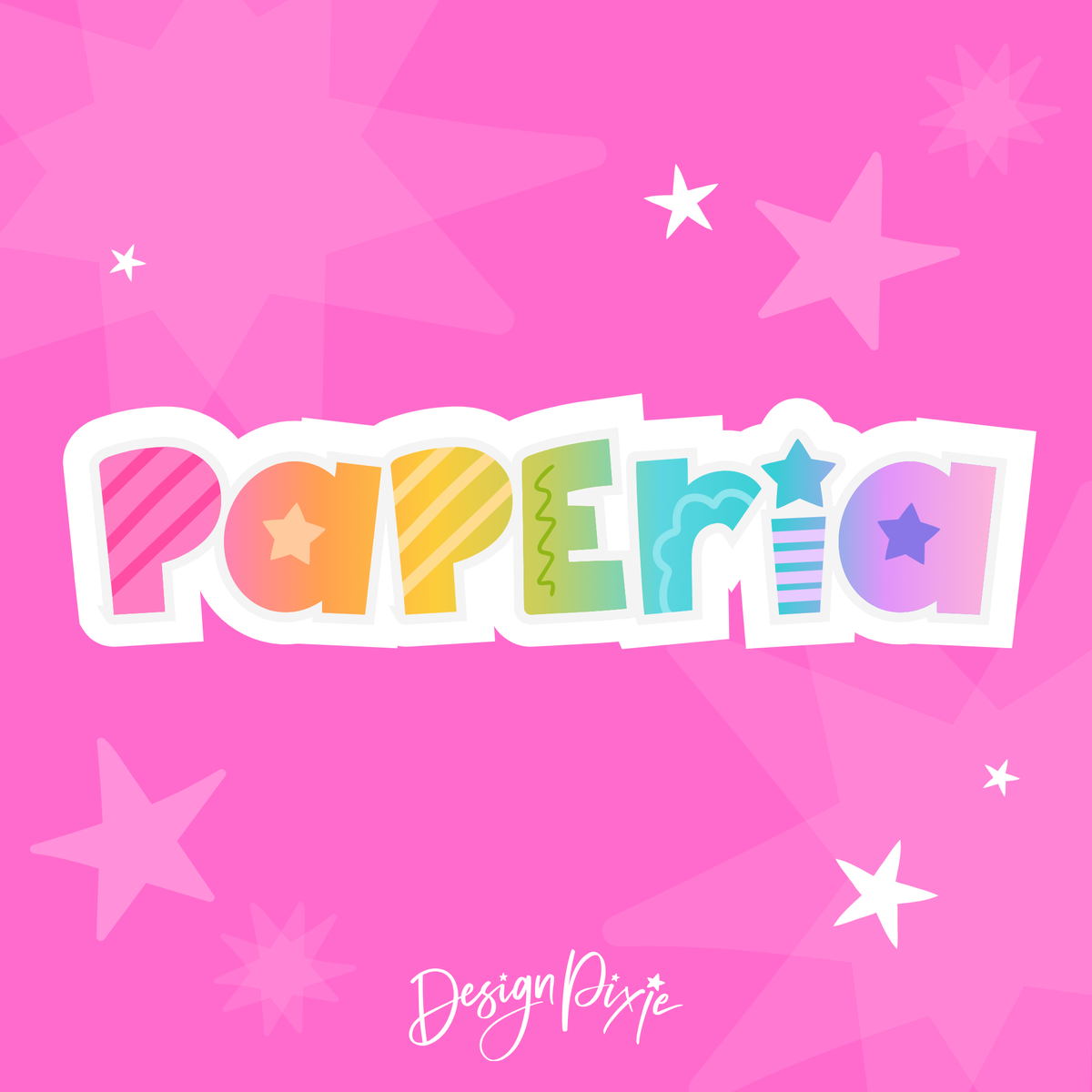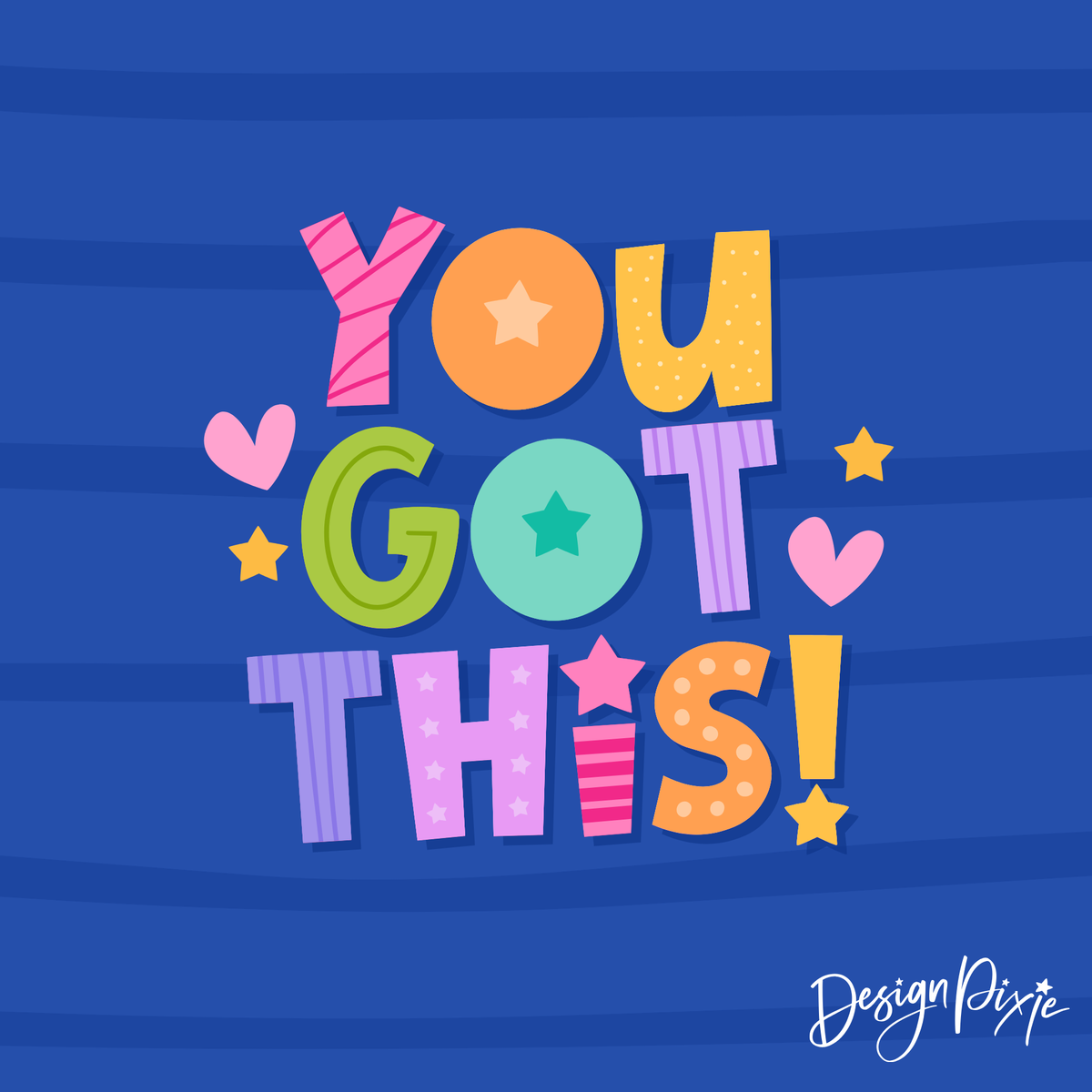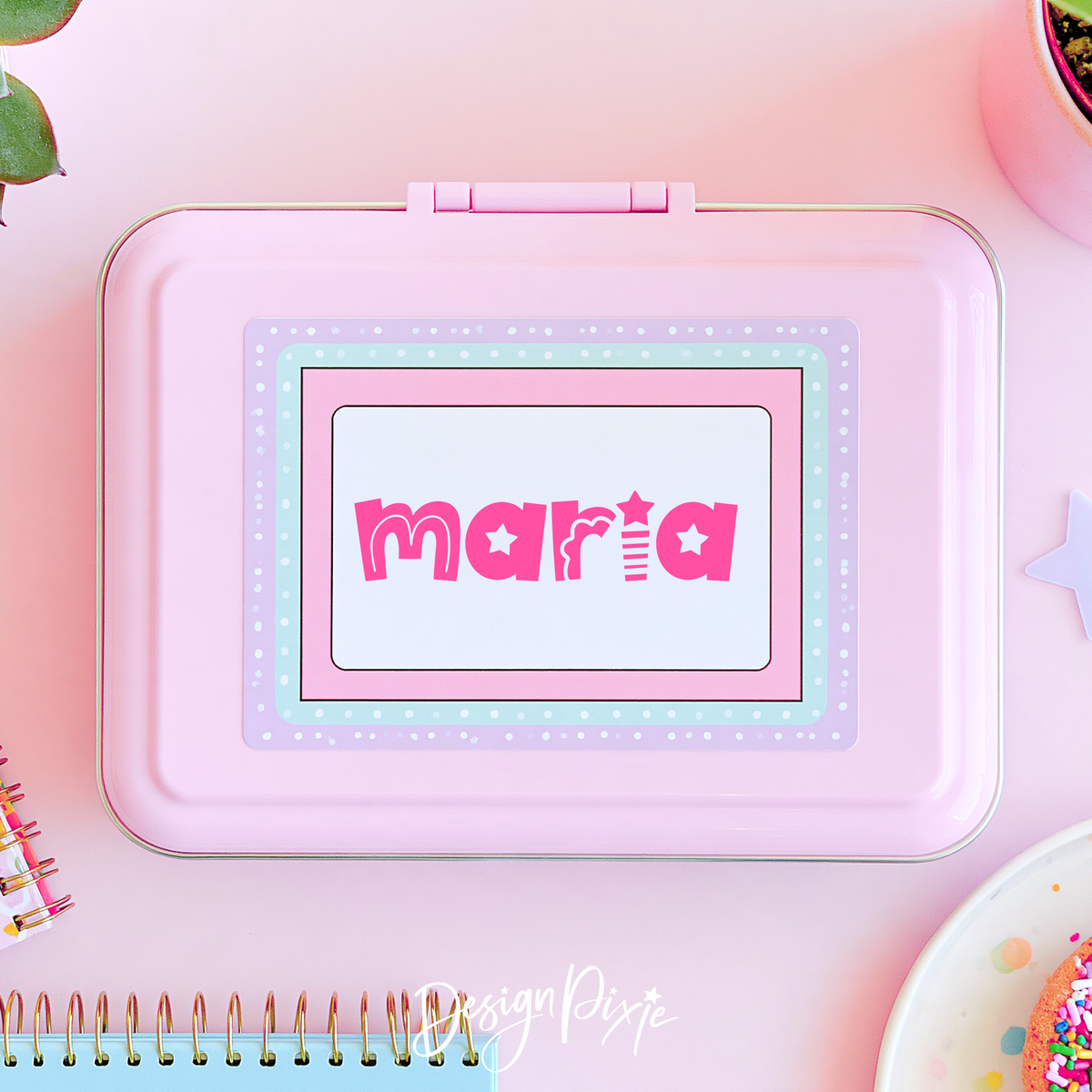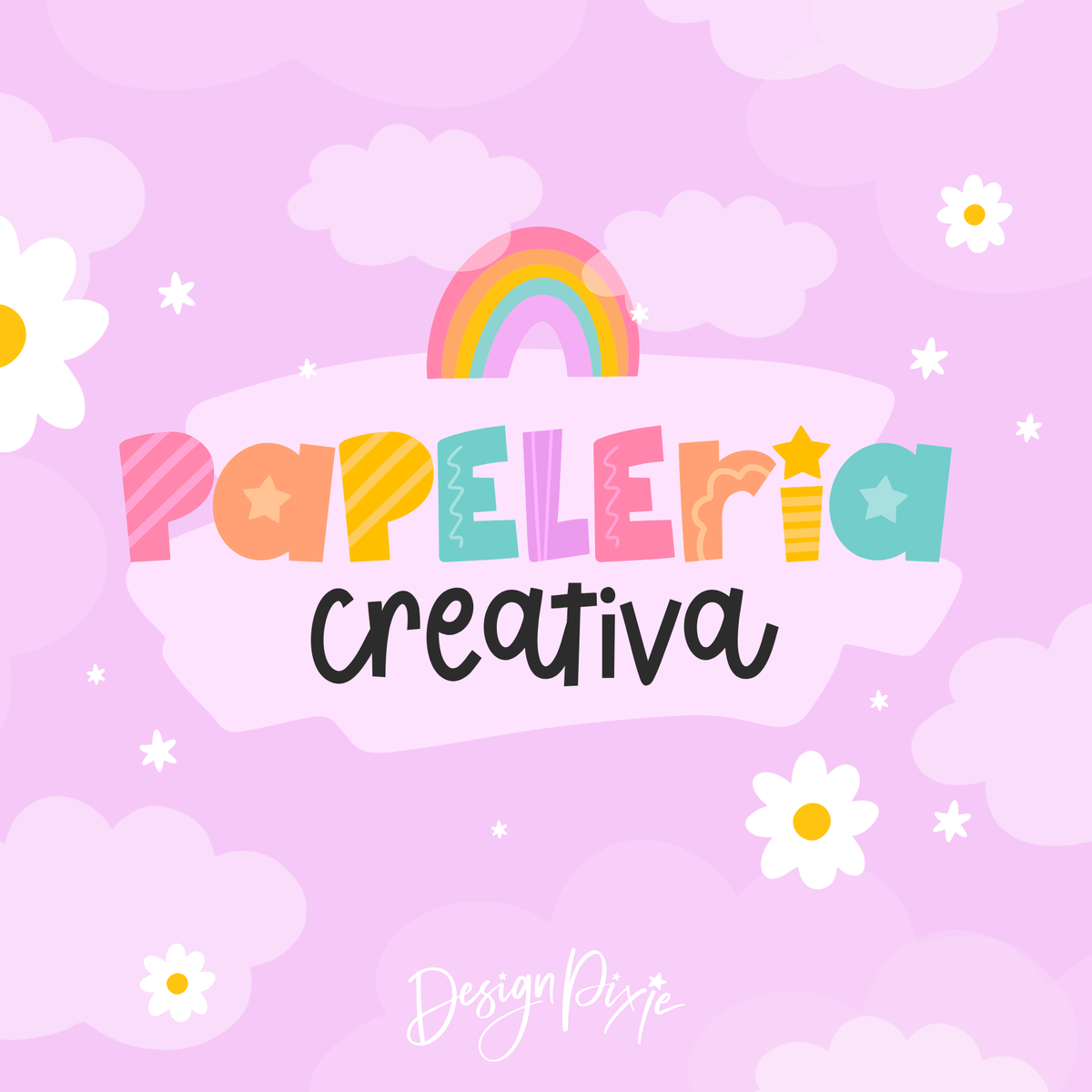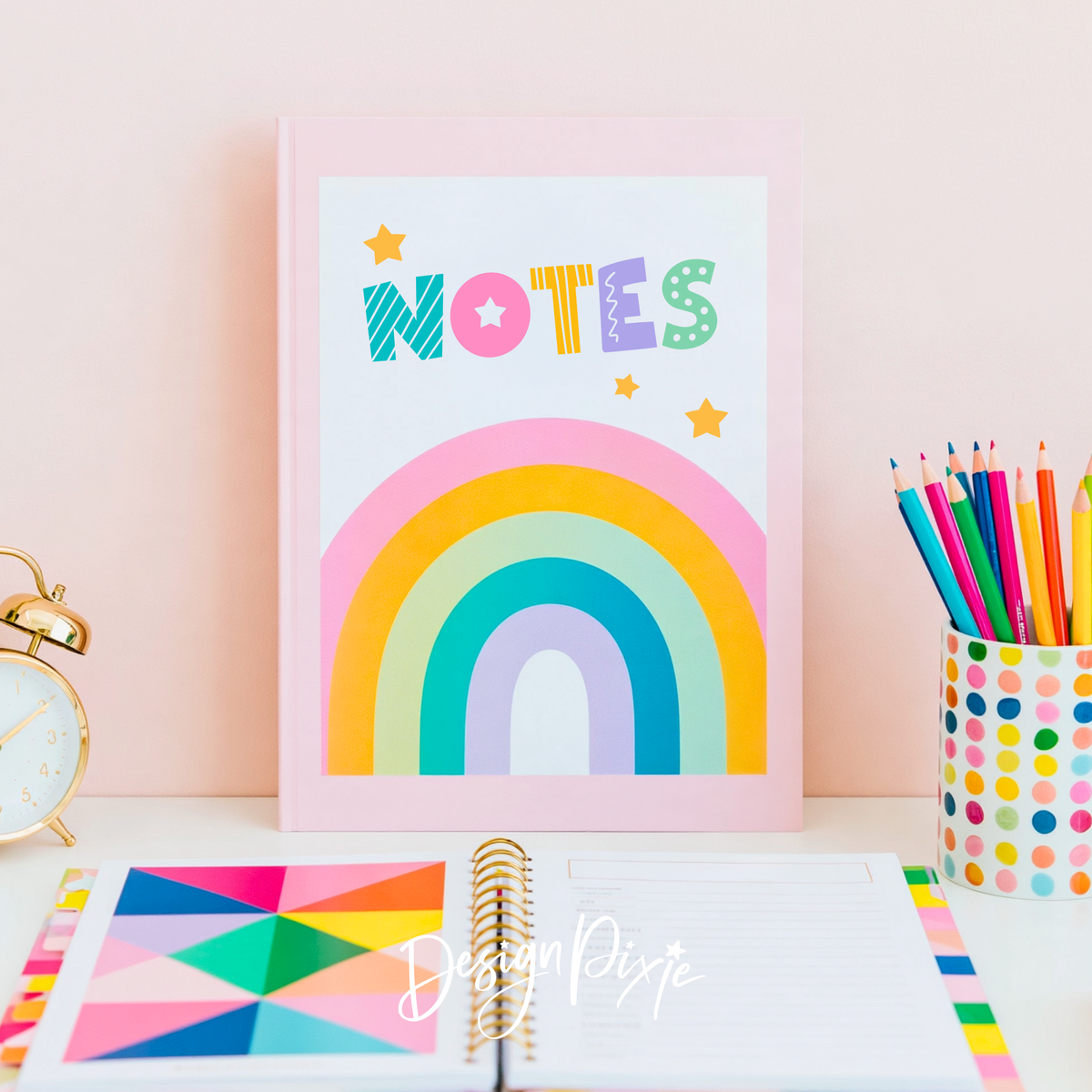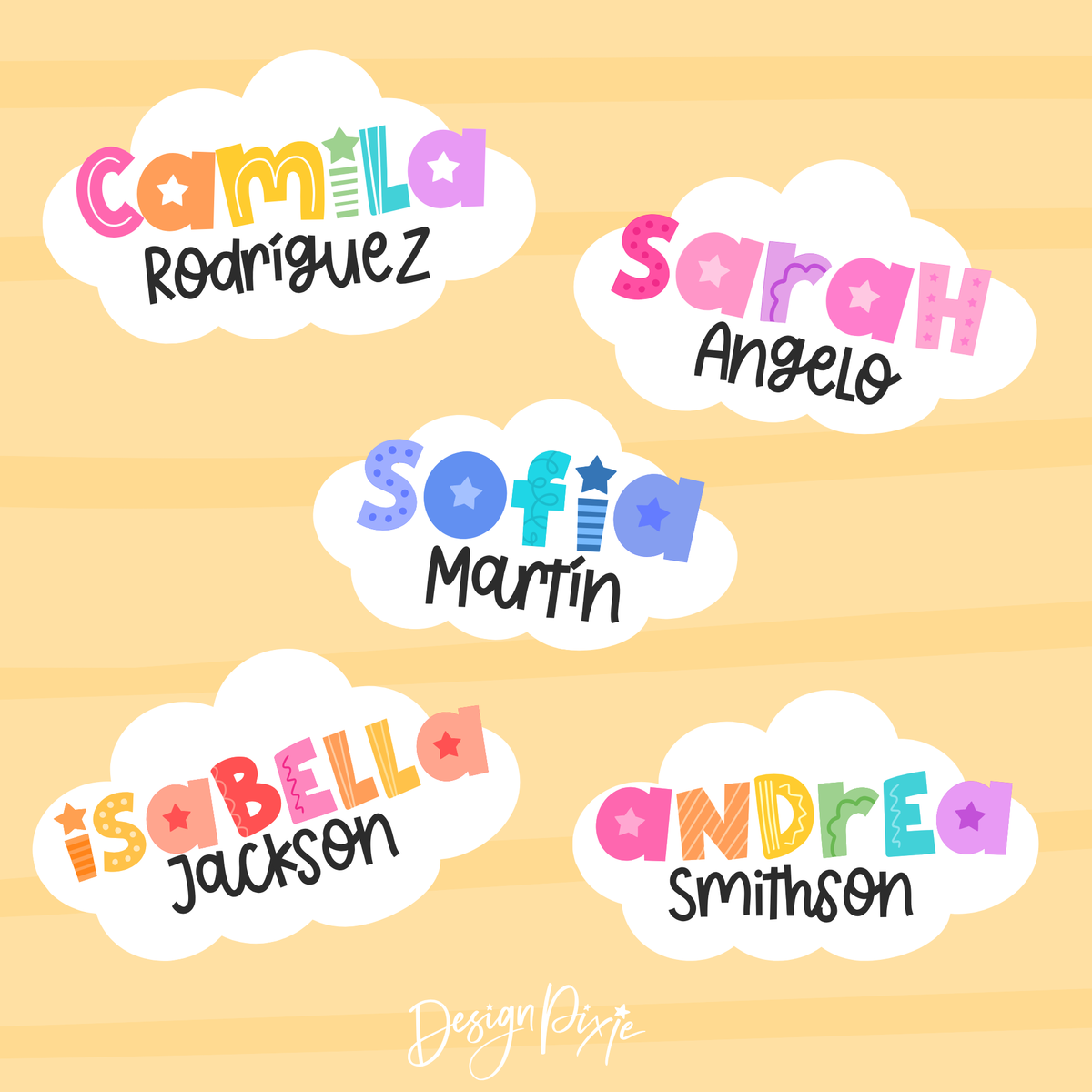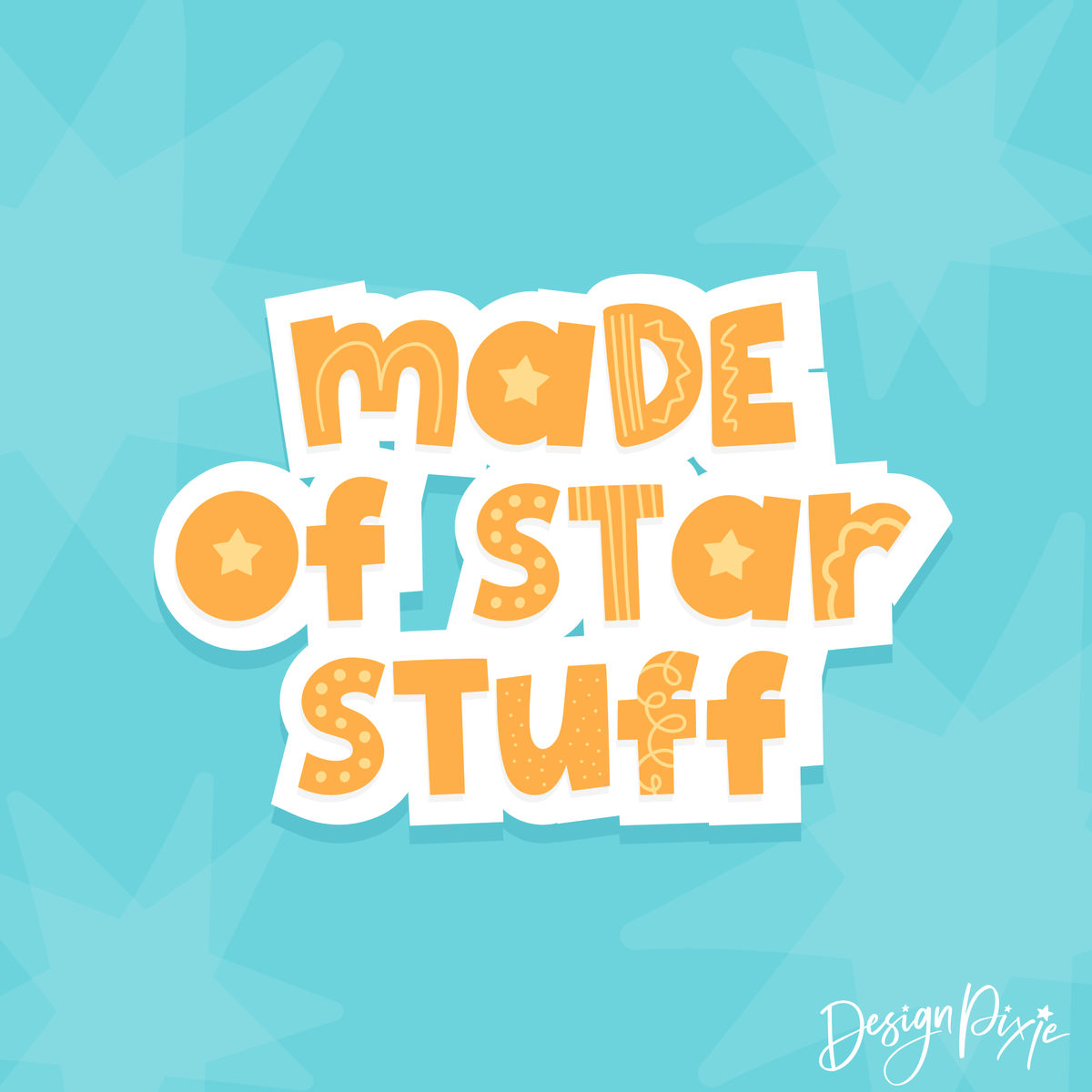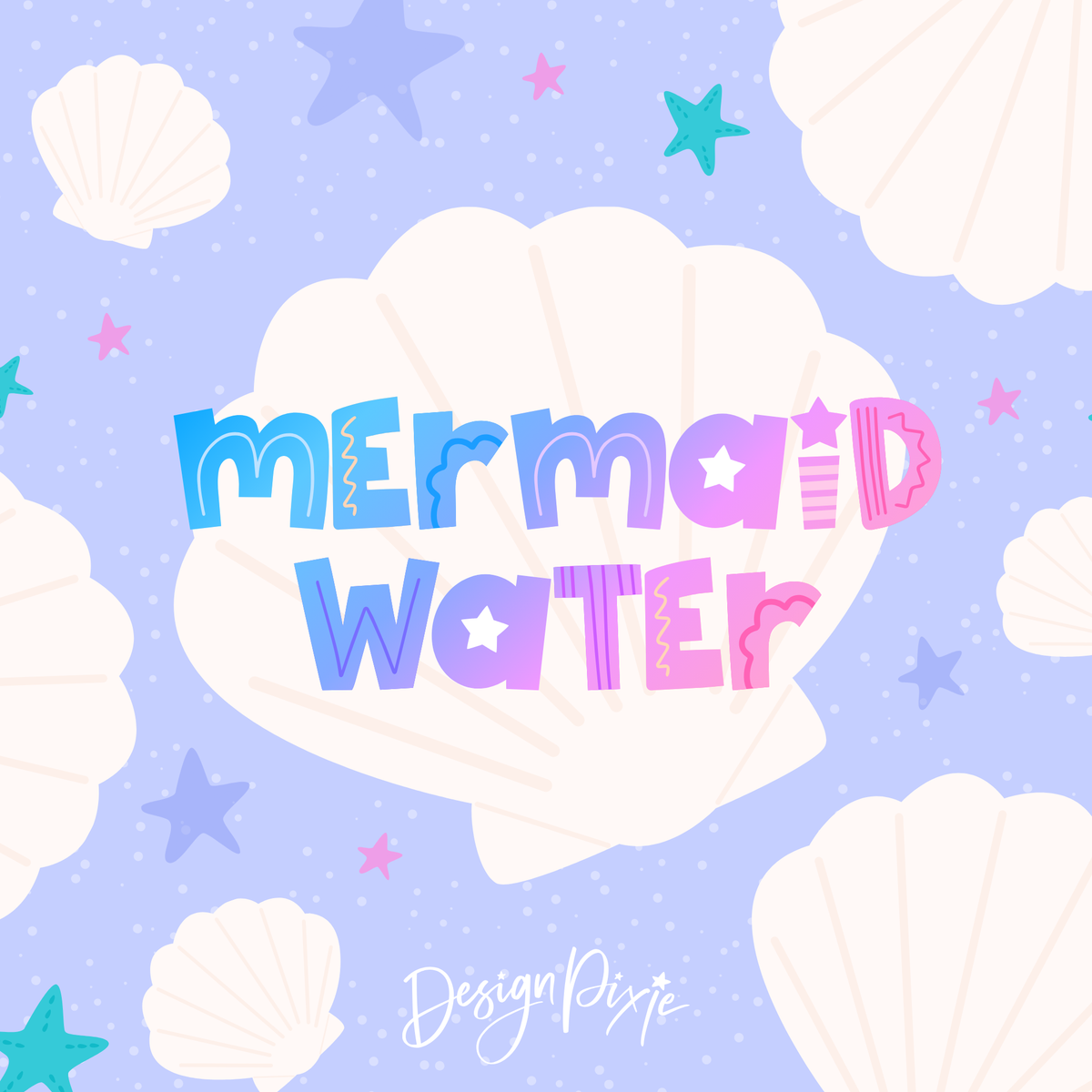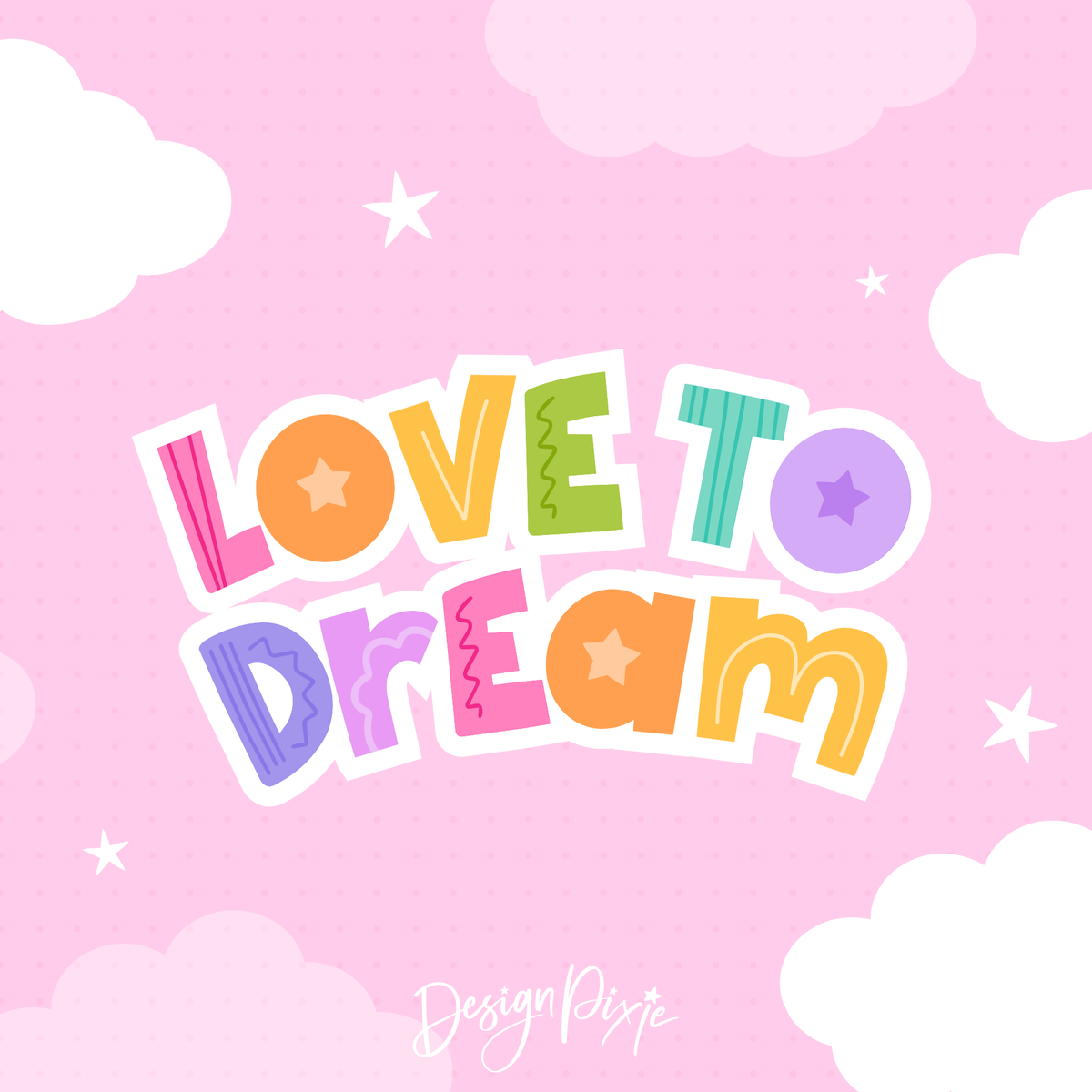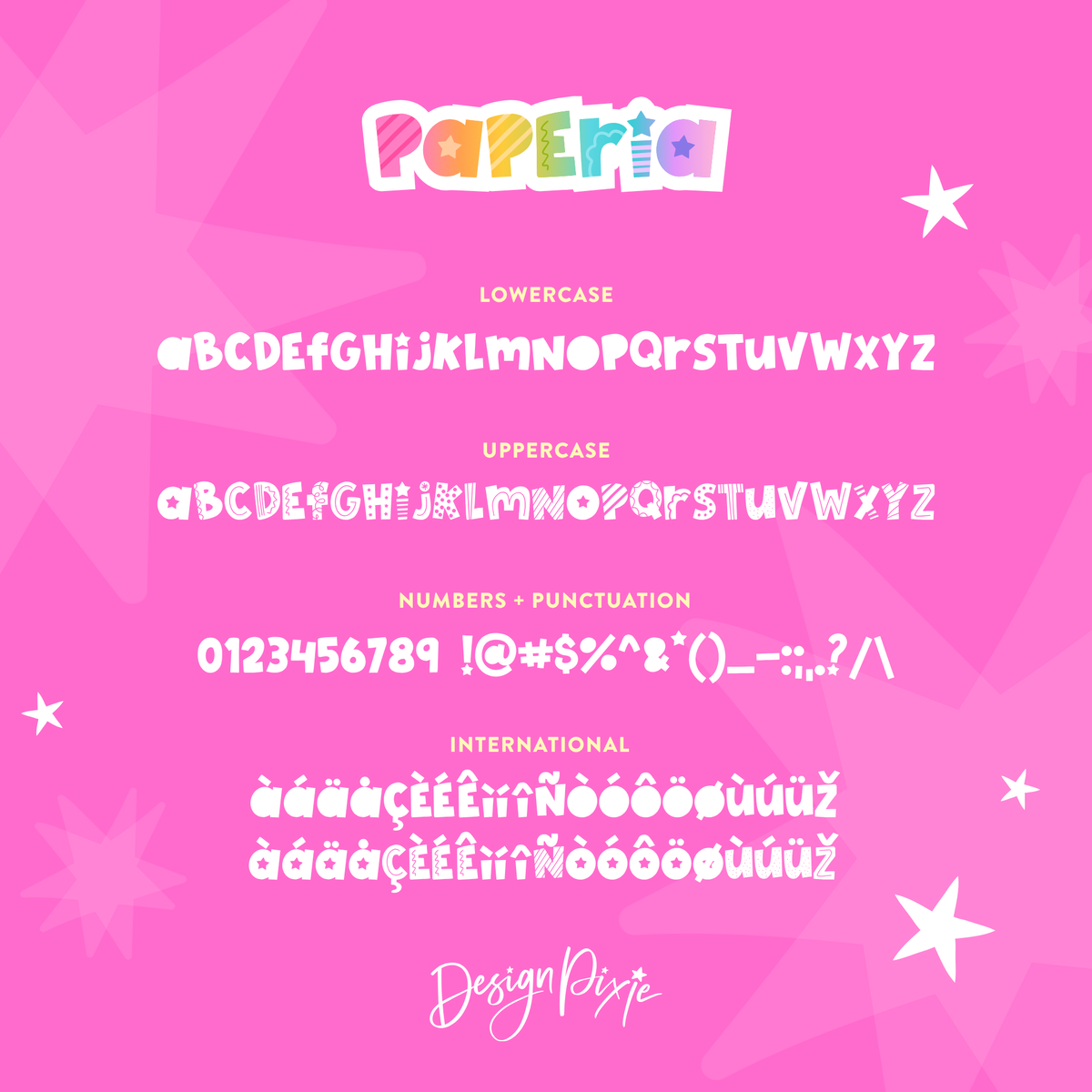
Fuente Paperia
Paperia es una tipografía decorativa y llamativa con patrones divertidos, letras gruesas y mucha personalidad. Diseñada para que tu tipografía destaque, esta fuente divertida con patrones combina letras minúsculas limpias con caracteres mayúsculas llamativos decorados con estrellas, rayas, puntos y garabatos.
Paperia incluye un conjunto de caracteres con una mezcla de letras minúsculas y mayúsculas. Las letras minúsculas son simples y sencillas, mientras que las mayúsculas presentan los patrones decorativos, lo que te permite combinar fácilmente tu tipografía y crear un aspecto divertido y personalizado.
Perfecta para
Paperia es una tipografía versátil para proyectos de Canva, Cricut y Silhouette, branding de pequeñas empresas, logotipos, prendas de vestir, pegatinas, papelería y diseños digitales. Sus letras gruesas funcionan especialmente bien para encabezados, frases cortas, citas y tipografía llamativa.